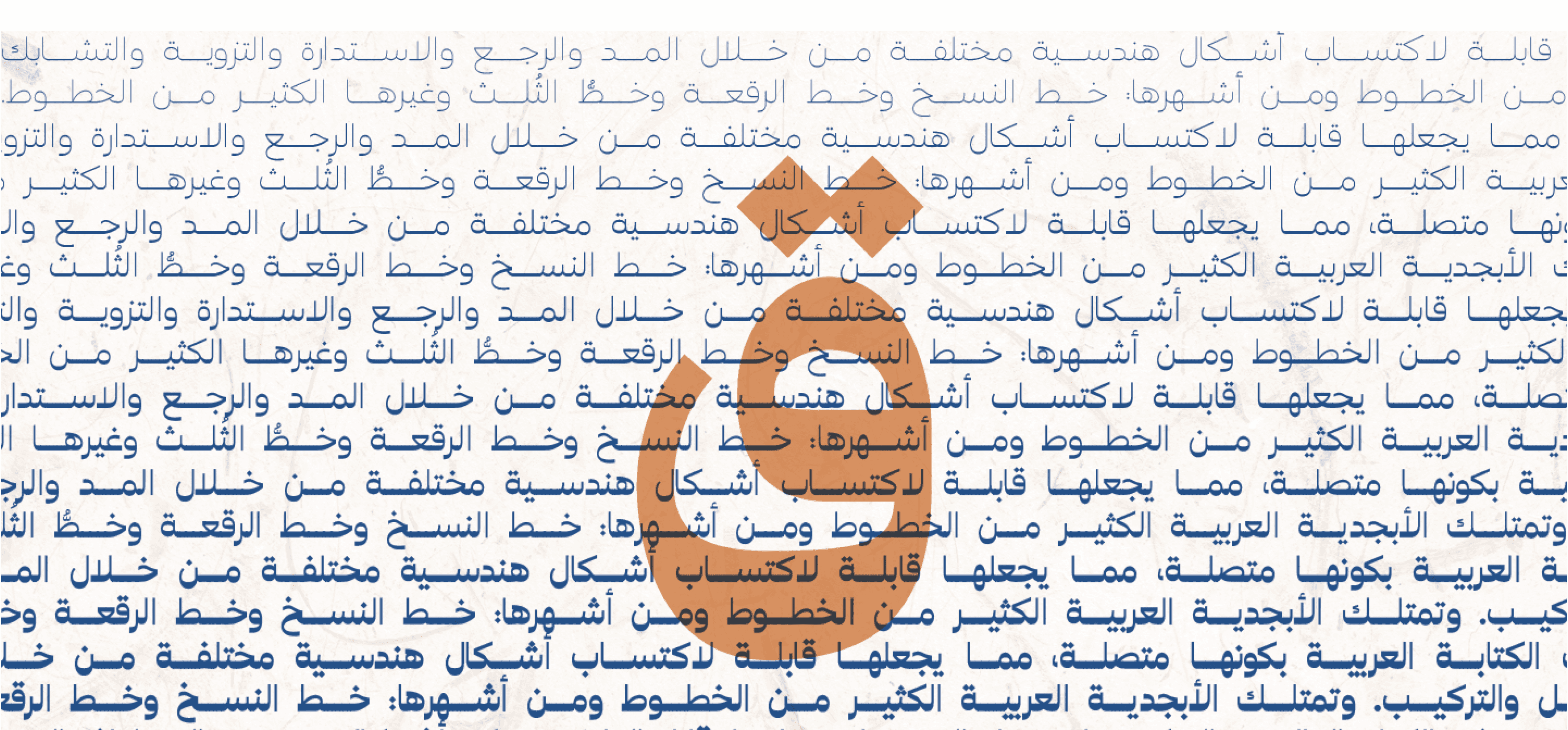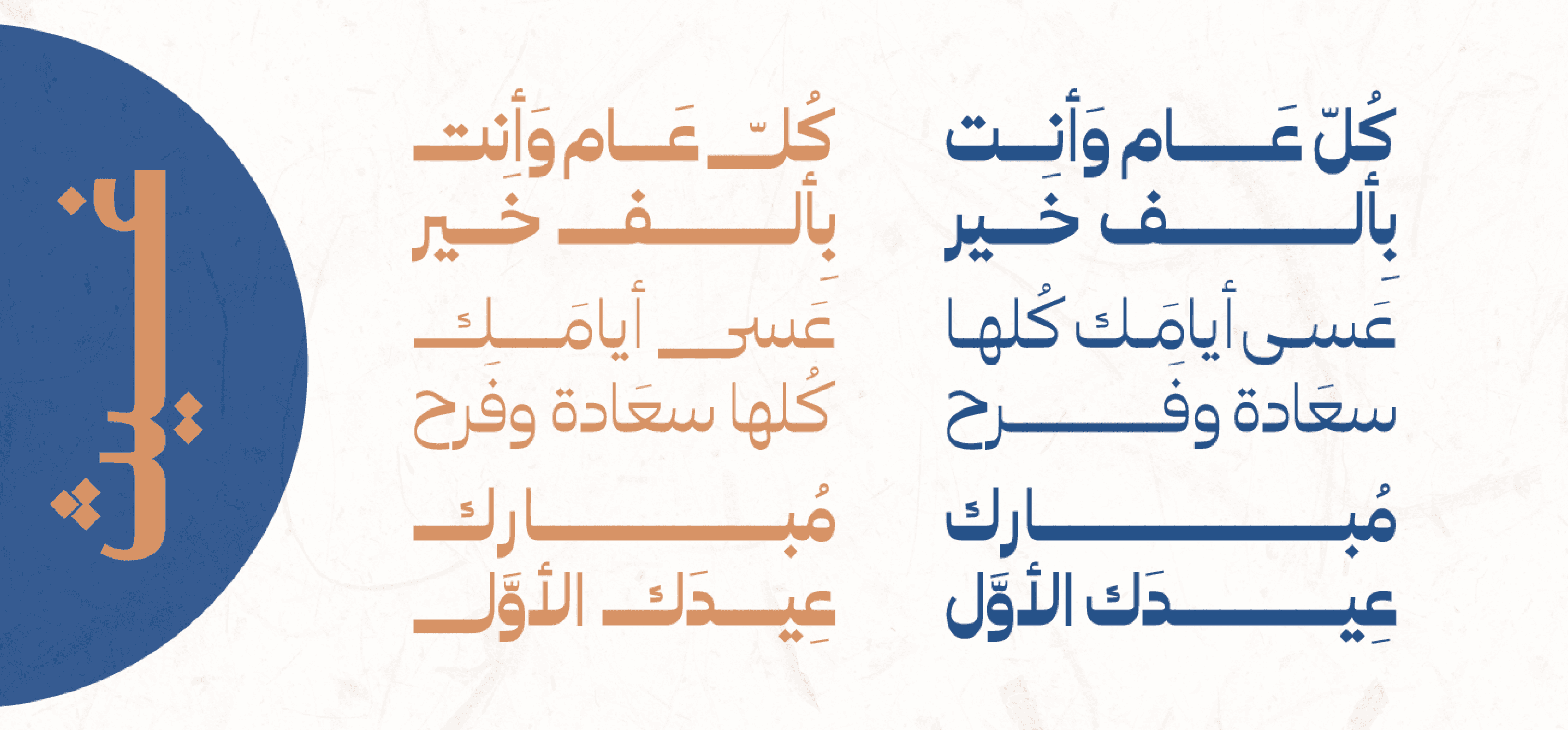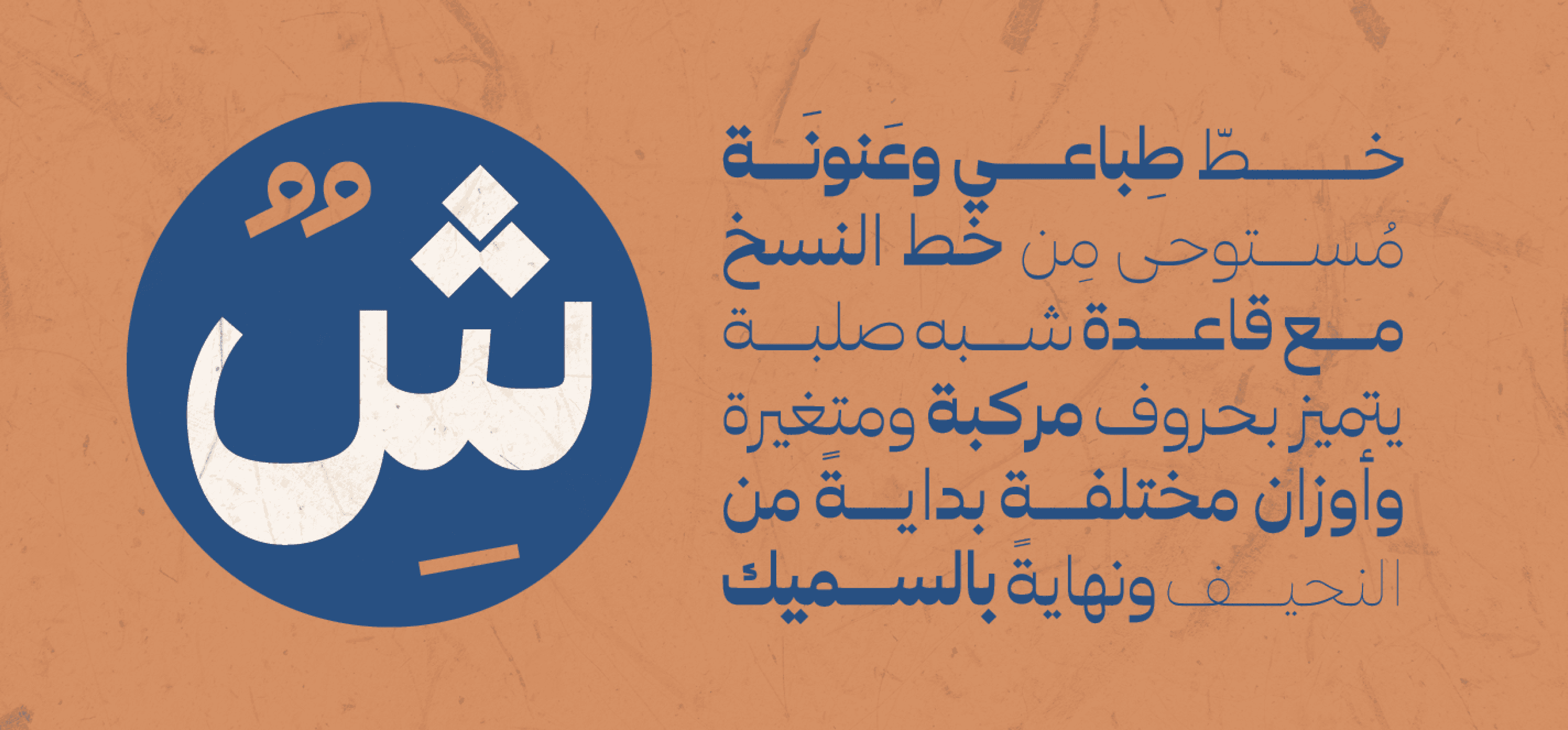
خط عربي مستوحى من أسلوب النسخ، يجمع بين البساطة والوضوح في تصميم عصري يدعم اللغتين العربية واللاتينية.
أُطلق في عام 2022، ويُعد خيارًا مثاليًا للتصاميم التحريرية، واجهات المستخدم، والمطبوعات التي تتطلب وضوحًا وأناقة في آنٍ واحد.
بفضل توازن الحروف ودقتها البصرية، يقدم "غيث سانس" تجربة قراءة مريحة وعصرية تناسب الاستخدام المهني والتجاري.